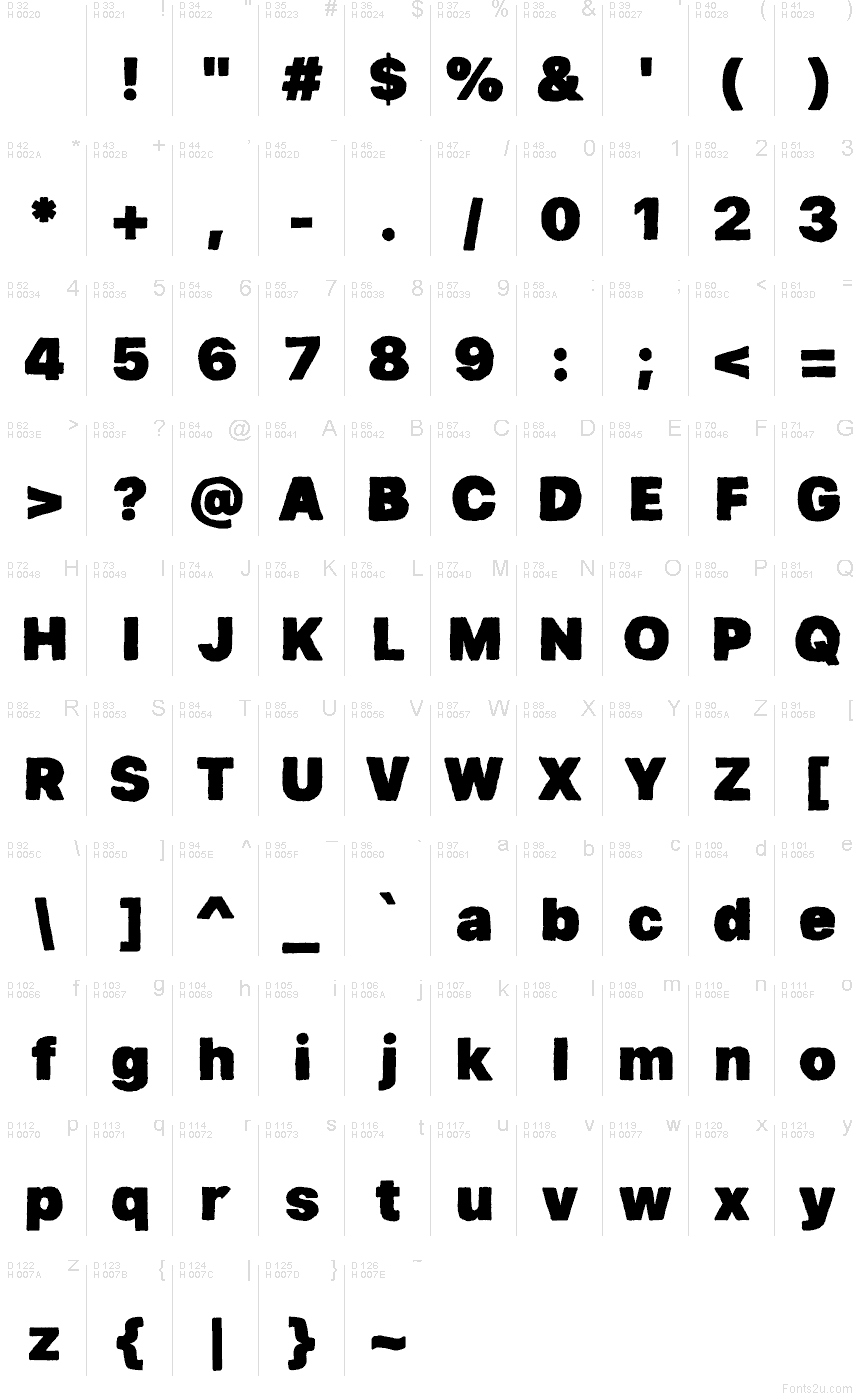
Horeg Bolot
Шрифт Horeg Bolot від Hello Good Studio - це безкоштовний декоративний шрифт з ефектом ерозії, заокругленими нерівними літерами та грубими вирізаними краями. Форми виглядають так, ніби їх вирізали вручну, а не створювали геометрично, а текстуроване оздоблення надає кожному знаку цілісного вигляду.
Horeg Bolot чудово підходить для заголовків плакатів, обкладинок альбомів, флаєрів, графіки на одязі та логотипів, яким потрібен потертий графічний стиль. Цей безкоштовний шрифт також добре пасує для вивісок і коротких рекламних текстів, де пошкоджена поверхня надає літерам грубого «штампованого» вигляду, не перешкоджаючи читанню.